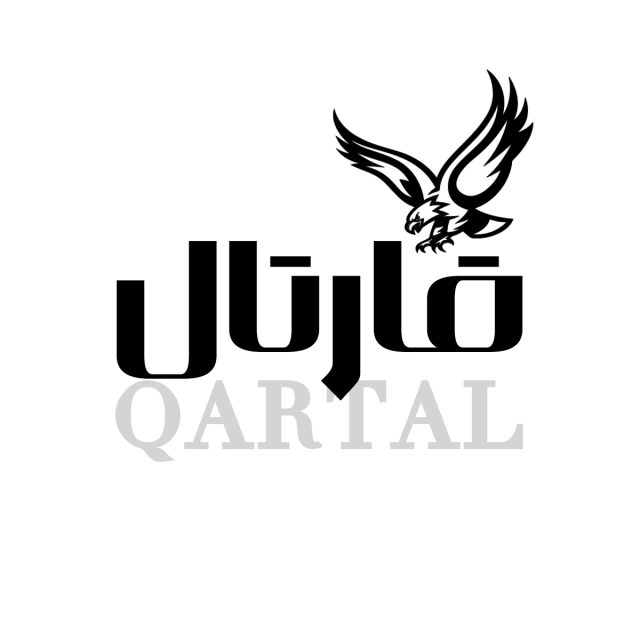
فونت فارسی قارتال Qartal Font
فونت فارسی قارتال برای استفاده در اکثر آثار تبلیغاتی به ویژه برای لوگوتایپ و کسب و کارهای خلاق و نوین بسیار مناسب است. فونت قارتال به…
فونت فارسی قارتال: فونت قارتال اثر هاشم شهرزاد یک فونت هندسی و نمایشی است. این فونت بیشتر مناسب موضوعات تجاری و تبلیغاتی و مدرن از قبیل کاور و اسلاید شبکههای اجتماعی و تبلیغات و بسته بندی میباشد. قارتال با توجه به هندسی بودن، چهره مدرن و شبیه لاتین دارد به طوری که راستای عمودی ضخیم و راستای افقی نازک است.
فونت لوگوتایپ قارتال
فونت فارسی قارتال برای استفاده در اکثر آثار تبلیغاتی به ویژه برای لوگوتایپ و کسب و کارهای خلاق و نوین بسیار مناسب است. فونت قارتال به صورت تک وزن طراحی شده است که علاوه بر تمام حروف و اعداد فارسی، از فونت مکمل انگلیسی اختصاصی نیز در آن استفاده شده است تا در متن های فارسی، انگلیسی نیازی به تغییر فونت نداشته باشید.
کاربردهای فونت قارتال
- مناسب طراحی بسته بندی ها
- فونت تولید محتوا
- فونت فارسی طراحی وب
- مناسب استفاده در تابلو ها و بنر ها
پیشنمایش ها و نمونه تایپ هایی از فونت فارسی قارتال